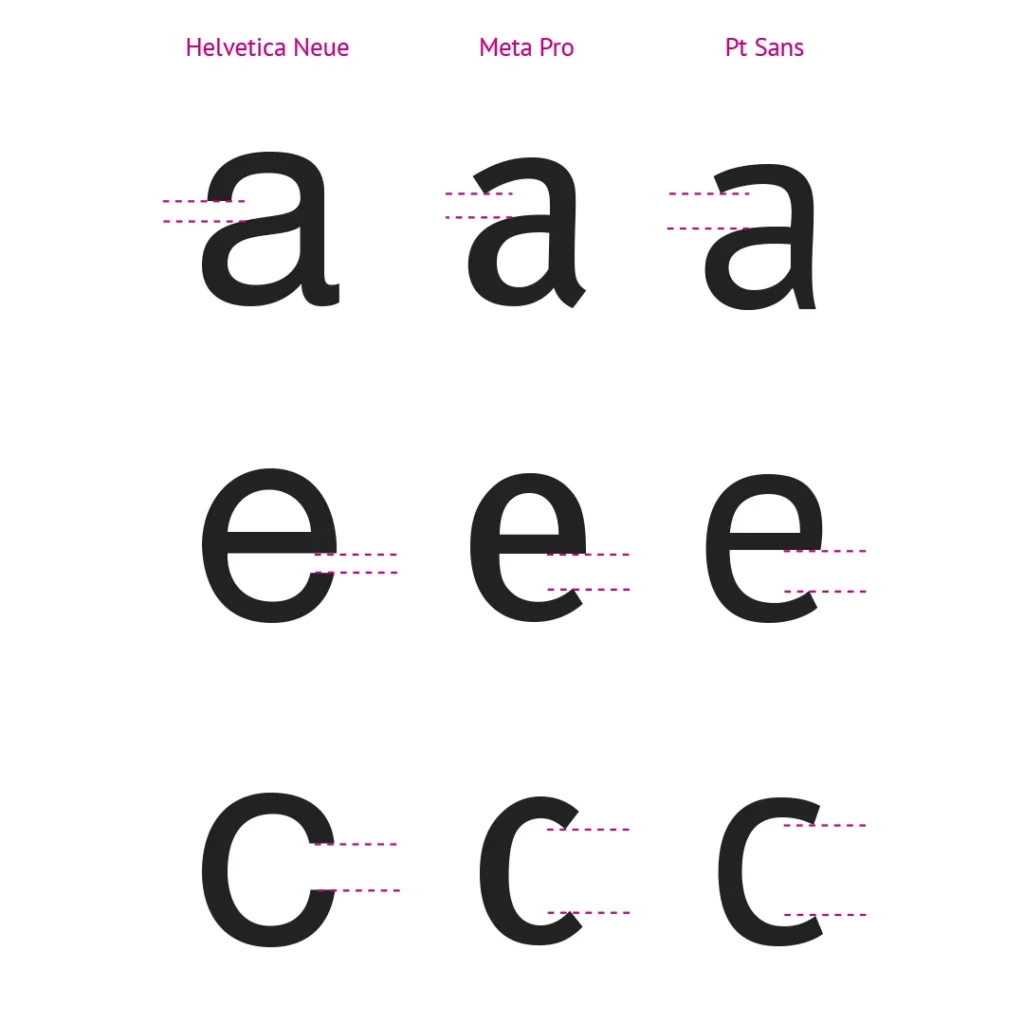
APERTURA
Se llama apertura a las formas abiertas que pueden presentar algunas letras.
La amplitud o la estrechez de la apertura define el estilo de la tipografía, así como influye en su legibilidad.